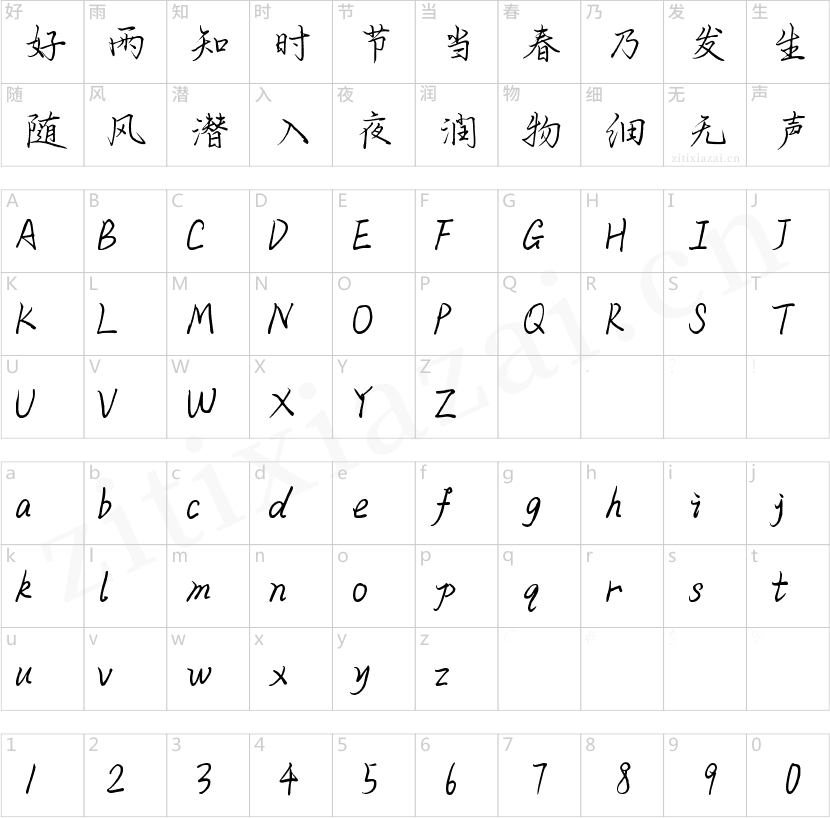
Aa星玥体
Aa星玥体字体
Aa星玥体是一款非常具有艺术性的字体,它的设计灵感来源于对古典艺术的研究,同时又融入了现代字体设计的元素。字形优美,笔画粗细变化自然,给人以大气、典雅的感觉。Aa星玥体是一款既传统又现代的字体,它的设计充满艺术感,美观大方,实用性也非常强。无论是对于设计师还是对于普通读者来说,都是一种非常不错的字体选择。Aa星玥体适合用于具有艺术感的场合,比如海报、宣传单张、书籍封面等。由于其字形流畅且具有动态感,也适合用于大量的文本排版,如报纸、杂志等。